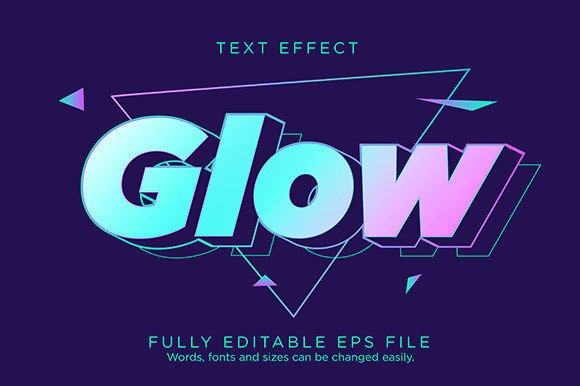
Triangle Glow Text Effect Font Type
Triangle Glow Text Effect Font Type와 같은 κ³ ν’ˆμ§ˆ μžμ‚°μ„ μ°Ύκ³  μžˆλ‹€λ©΄ 이 프리미엄 νŒ¨ν‚€μ§€λŠ” 창의적인 ν”„λ‘œμ νŠΈλ₯Ό μœ„ν•œ ν™˜μƒμ μΈ μ„ νƒμž…λ‹ˆλ‹€.
μ •λ°€ν•˜κ²Œ μ œμž‘λœ Triangle Glow Text Effect Font TypeλŠ” κΉ”λ”ν•œ 벑터, λΆ€λ“œλŸ¬μš΄ νƒ€μ΄ν¬κ·Έλž˜ν”Ό 및 μ•ˆμ‹¬ν•  수 μžˆλŠ” μƒμ—…μš© λΌμ΄μ„ μŠ€λ₯Ό μ œκ³΅ν•©λ‹ˆλ‹€.
POD(μ£Όλ¬Έν˜• 인쇄) μ œν’ˆ, κ²°ν˜Όμ‹ μ΄ˆλŒ€μž₯ λ˜λŠ” μ†Œμ…œ λ―Έλ””μ–΄ κ·Έλž˜ν”½μ„ λ§Œλ“€ λ•Œ Triangle Glow Text Effect Font TypeλŠ” 이상적인 μ„ νƒμž…λ‹ˆλ‹€.
μ „λ¬Έκ°€ 팁: μ΄λŸ¬ν•œ μš”μ†Œλ₯Ό 보완 κΈ€κΌ΄κ³Ό κ²°ν•©ν•˜μ—¬ μ‹œμž₯μ—μ„œ λˆˆμ— λ„λŠ” λ…νŠΉν•˜κ³  λˆˆκΈΈμ„ λ„λŠ” λ””μžμΈμ„ λ§Œλ“­λ‹ˆλ‹€.
무료 λŒ€μ•ˆμ΄ μ‘΄μž¬ν•˜μ§€λ§Œ μ’…μ’… Triangle Glow Text Effect Font Type에 μžˆλŠ” 상업적 κΆŒλ¦¬μ™€ 기술적 완성도가 λΆ€μ‘±ν•©λ‹ˆλ‹€.